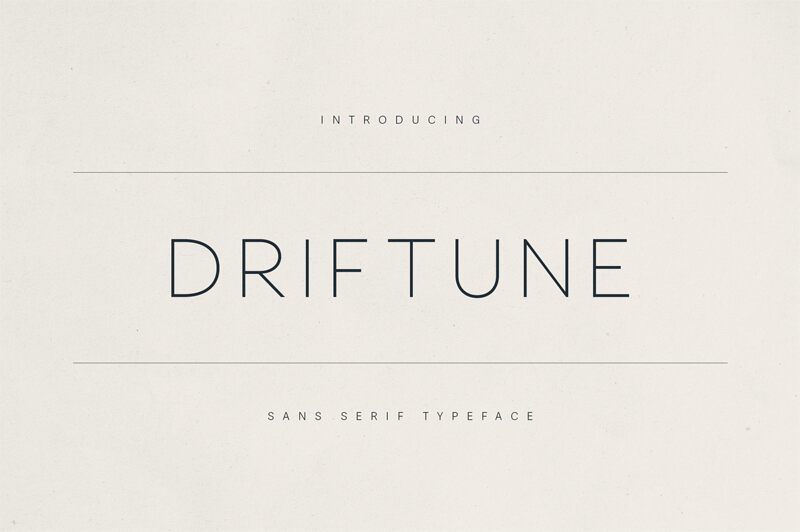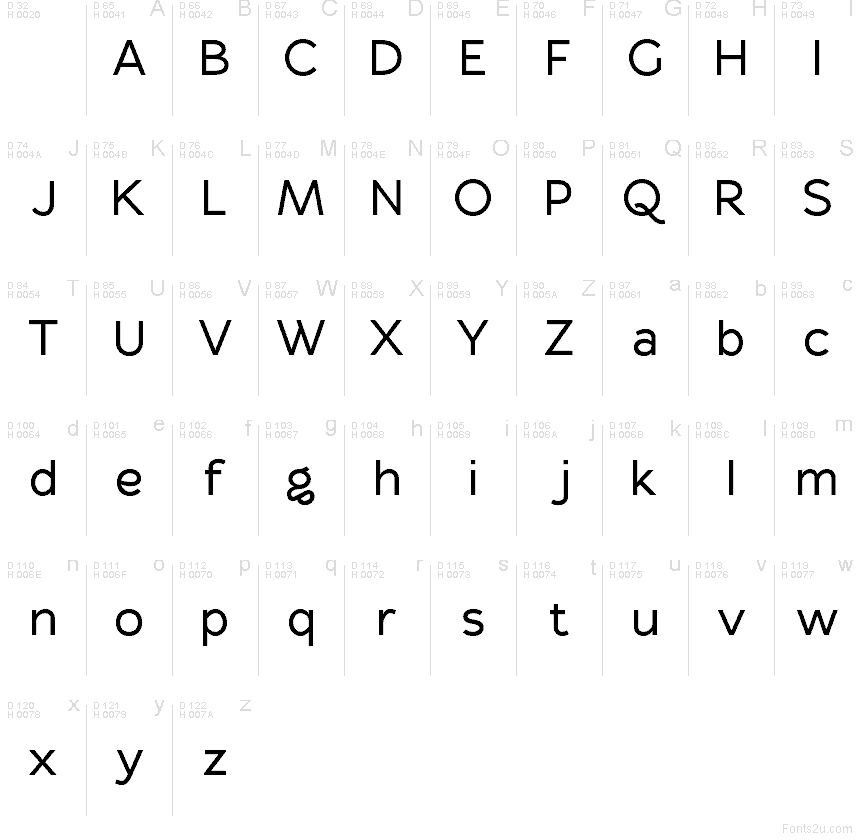
Driftune SemiBold ist eine kostenlose serifenlose Schrift mit einer hohen, reduzierten Silhouette und einem spürbar ruhigen Rhythmus. Die geraden Vertikalen, offenen Kurven und prägnanten Verbindungen verleihen dem Schriftbild eine minimalistische und aufgeräumte Anmutung, statt geometrisch oder übermäßig weich zu wirken.
Diese Zurückhaltung verleiht kurzen Titeln eine klare Präsenz auf Postern, Magazincovern, Buchtiteln, App-Splash-Screens und Marken-Headern. Sie eignet sich zudem hervorragend für Verpackungen und redaktionelle Zitate, bei denen die aufrechte Struktur und die unaufdringliche Wirkung der Schrift das Layout strukturieren, ohne den Design-Stil zu dominieren.